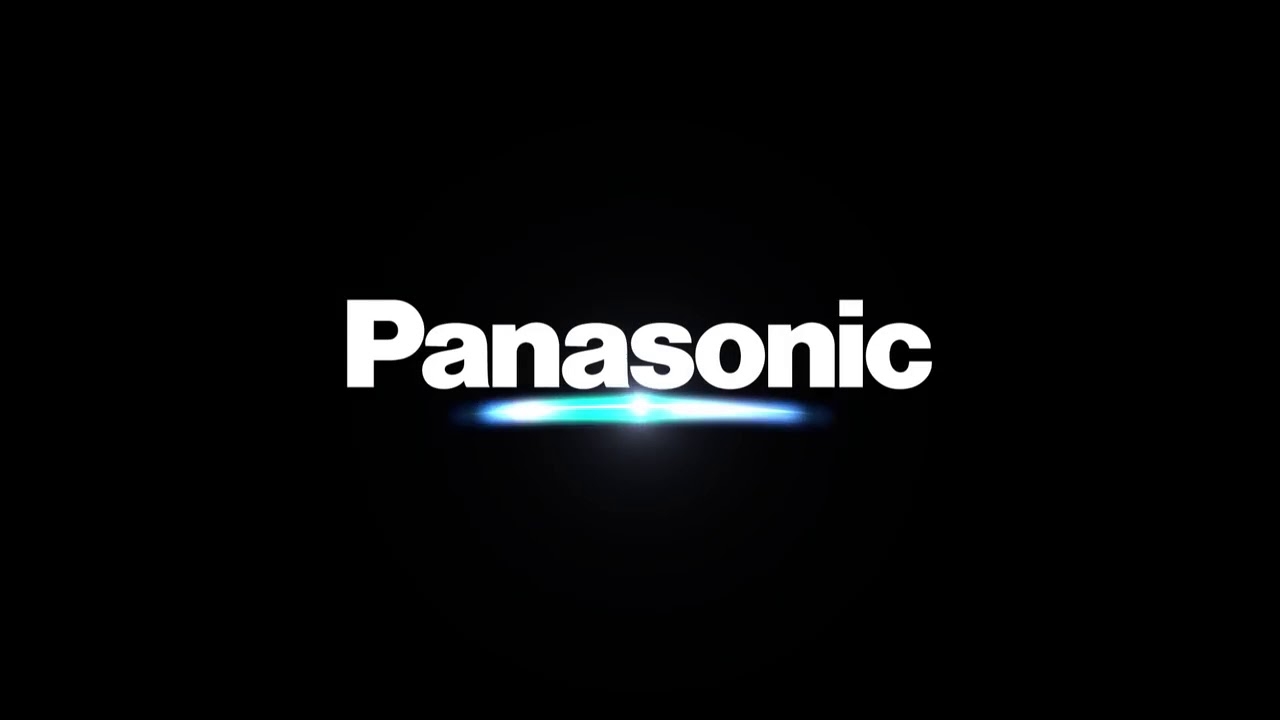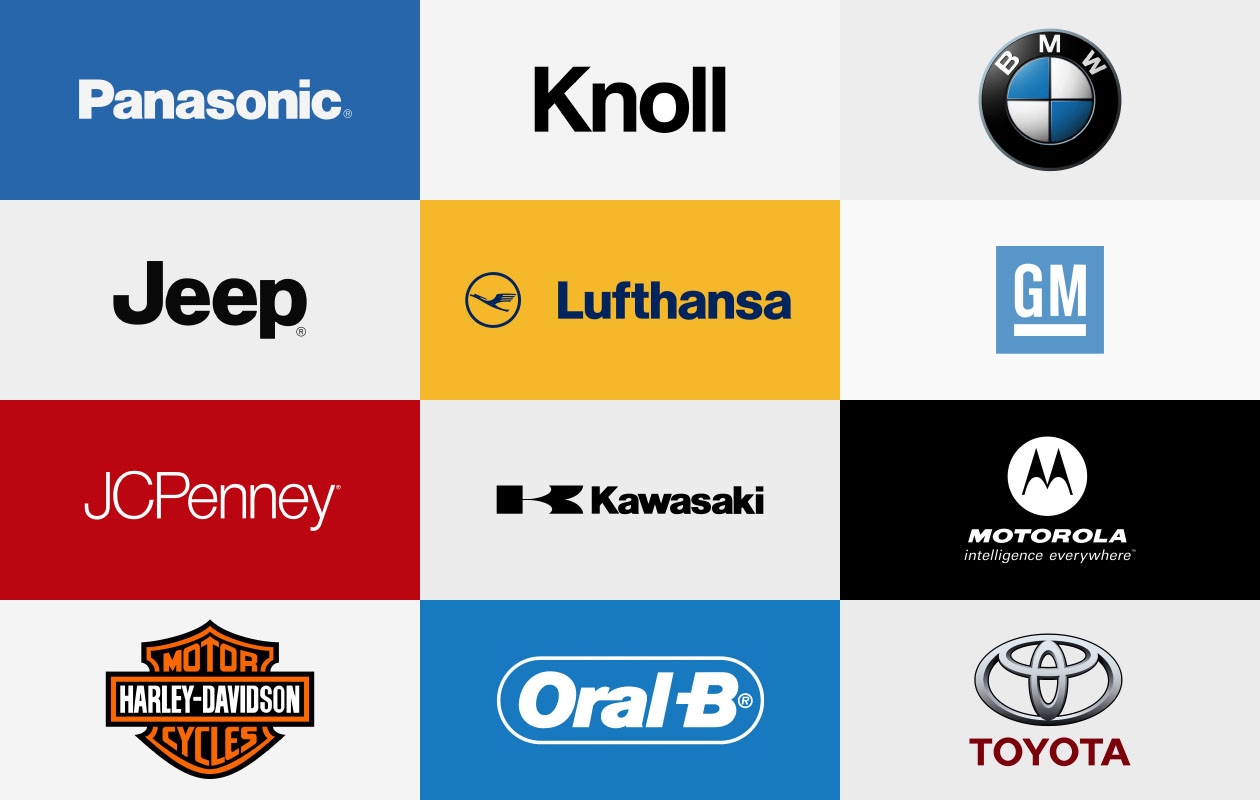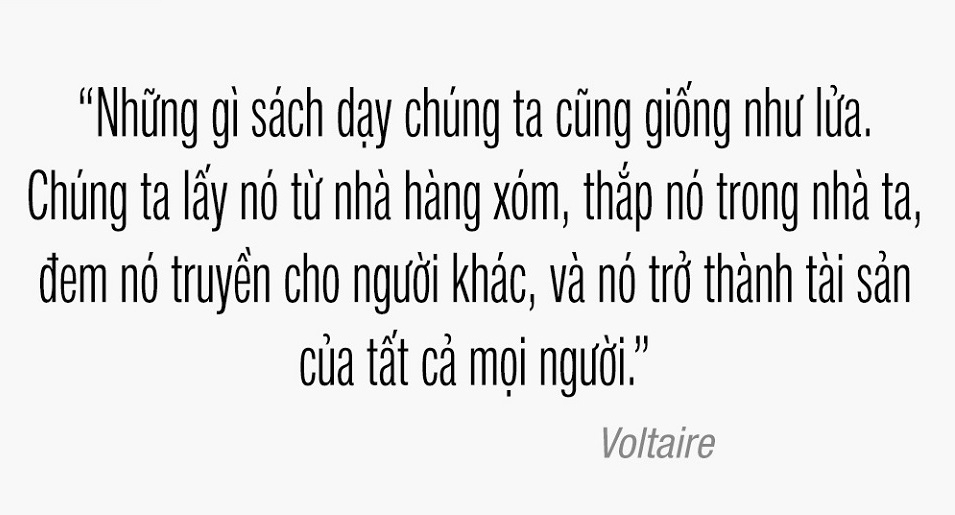
Khám phá và tải về bộ font Helvetica được Việt hoá - biểu tượng của sự tối giản trong thiết kế!
Trong thế giới thiết kế chữ và đồ họa, font Helvetica đã trở thành một biểu tượng, một font chữ toàn cầu được ưa chuộng bởi độ đơn giản, sạch sẽ và dễ đọc. Cùng tìm hiểu về nguồn gốc và đặc điểm của font Helvetica và tải về máy tính bộ font Helvetica được Việt hoá trong bài viết dưới đây!
Lịch sử và nguồn gốc của font Helvetica
Giới thiệu về font Helvetica
Trong thế giới đồ họa và thiết kế, font chữ đóng vai trò quan trọng trong việc truyền đạt thông điệp và tạo nên sự thẩm mỹ cho một sản phẩm. Một trong những font chữ phổ biến và được sử dụng rộng rãi nhất trong lĩnh vực này là Helvetica. Helvetica là một font chữ sans-serif (không có gạch chân) với thiết kế đơn giản và dễ đọc. Nó đã trở thành biểu tượng của sự tối giản và tính thời thượng trong thiết kế.
Lịch sử và nguồn gốc của font Helvetica
Font Helvetica được tạo ra vào cuối những năm 1950 nhờ sự hợp tác giữa hai nhà thiết kế font chữ người Thụy Sĩ là Max Miedinger và Eduard Hoffmann. Năm 1957, font chữ này được chính thức ra mắt bởi nhà máy chữ Haas ở Münchenstein, Thụy Sĩ, với tên gọi ban đầu là Neue Haas Grotesk. Tuy nhiên, vào năm 1960, nó chính thức đổi tên thành Helvetica, lấy cảm hứng từ từ Latin "Helvetica," có nghĩa là Thụy Sĩ. Sự xuất hiện của Helvetica đánh dấu một bước tiến trong lĩnh vực font chữ, bỏ qua những kiểu chữ trang trí và phức tạp của thời đó, mang đến một phong cách đơn giản và gọn gàng hơn.
Đặc điểm và thiết kế
Đặc điểm của font Helvetica
Font Helvetica có những đặc điểm nổi bật đã làm cho nó trở thành một font chữ phổ biến và được ưa chuộng. Đầu tiên, nó có thiết kế đơn giản và không có những chi tiết phức tạp, giúp nó dễ đọc và thích hợp cho nhiều mục đích sử dụng. Ngoài ra, nó cũng có khả năng chống nhòe, giúp cho các ký tự vẫn rõ nét và sắc sảo ngay cả ở kích cỡ nhỏ.
Font Helvetica có những đặc điểm cơ bản cụ thể sau:
- Độ cao x chiều cao được sử dụng để chỉ chiều cao của chữ viết thường.
- Các chữ in hoa có độ rộng đồng đều. Khác biệt hình dạng giữa các chữ cái không nổi bật - chúng đều giống nhau.
- Ký tự "S" có hình dạng vuông.
- Helvetica có các khe hẹp giữa các phần mở của các chữ cái, bao gồm c, f, h, v.v…, và các bên ngoài chữ cái.
- Khoảng cách giữa các chữ cái được thiết lập chặt chẽ, tạo nên vẻ dày đặc.
Thiết kế và cấu trúc của font Helvetica
Font Helvetica có một thiết kế cơ bản và đồng nhất, với các đường thẳng và góc cạnh mạnh mẽ. Nó không có các đường cong hoặc các chi tiết trang trí phức tạp, tạo nên một cảm giác gọn gàng và hiện đại. Điều này cũng giúp font Helvetica tương thích với nhiều phông chữ khác nhau và dễ dàng kết hợp với các yếu tố thiết kế khác.
Ứng dụng và tầm ảnh hưởng
Ứng dụng rộng rãi của font Helvetica
Font Helvetica đã trở thành một font chữ rất phổ biến và được sử dụng rộng rãi trong nhiều lĩnh vực khác nhau. Nó thường được sử dụng trong thiết kế đồ họa, quảng cáo, báo chí, in ấn, đồ họa trang web và nhiều ứng dụng khác. Font Helvetica đa dạng về kích cỡ và kiểu dáng, từ các phiên bản nhỏ gọn để sử dụng trong các tiêu đề đến các phiên bản mở rộng cho văn bản dài. Điều này làm cho nó phù hợp với nhiều loại dự án và mục đích sử dụng.
Tầm ảnh hưởng và sự lan rộng của font Helvetica
Font Helvetica đã có tầm ảnh hưởng to lớn đối với ngành thiết kế và trở thành một trong những font chữ phổ biến nhất trong lịch sử. Sự đơn giản và tính thời thượng của nó đã trở thành một tiêu chuẩn cho sự tối giản trong thiết kế. Nó đã ảnh hưởng đến nhiều font chữ sau này, các biến thể và phiên bản tương tự của font Helvetica đã được phát triển bởi các nhà thiết kế khác.
Font Helvetica cũng đã trở thành biểu tượng trong văn hóa đồ họa và ngay cả bên ngoài lĩnh vực thiết kế. Nó đã xuất hiện trong nhiều tác phẩm nghệ thuật, phim ảnh và quảng cáo nổi tiếng. Từ logo của American Airlines, hệ thống tàu điện ngầm của Thành phố New York đến bộ phim nổi tiếng "Helvetica" của Gary Hustwit, font chữ này đã chứng tỏ sự tồn tại và ảnh hưởng của nó trong cuộc sống hàng ngày.
Những sự thật thú vị xung quanh font Helvetica
Tại sao ta có thể bắt gặp font chữ Helvetica ở mọi nơi?
Font chữ Helvetica đã duy trì phong cách tối giản và tính hữu ích suốt nhiều năm và dự kiến sẽ tiếp tục được ưa chuộng trong tương lai. Tuy nhiên, điểm đặc biệt của Helvetica chính là sự không nổi bật. Nó không cầu kỳ hay quá sặc sỡ, đó chính là ưu điểm của loại font này. Helvetica dễ đọc mà không đòi hỏi sự tập trung đặc biệt, đó là lý do tại sao nó đã được sử dụng rộng rãi, bao gồm cả trong hệ thống biển chỉ dẫn của tàu điện ngầm ở Thành phố New York trong một thời gian dài.
Helvetica được gọi là “The Little Black Dress” của các kiểu chữ
"Little Black Dress" (LBD) là thuật ngữ chỉ một chiếc váy đen, đơn giản và cổ điển, được xem là một món đồ không thể thiếu trong tủ quần áo của mỗi phụ nữ. Thuật ngữ này được phổ biến bởi nhà thiết kế thời trang Coco Chanel trong những năm 1920 và trở thành biểu tượng của sự thanh lịch và đẳng cấp.